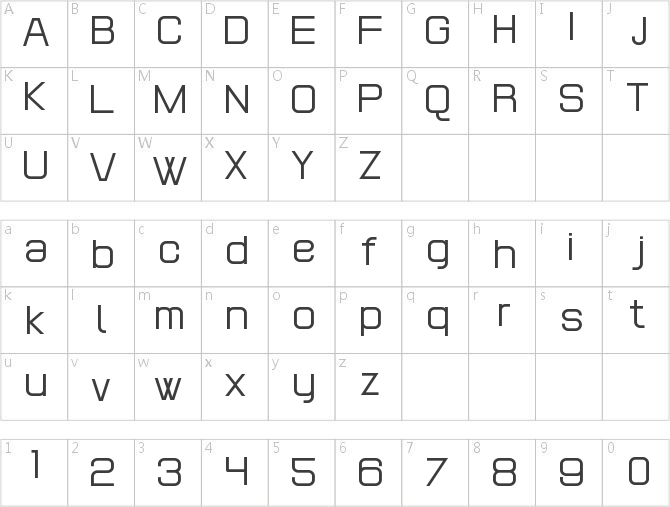
POE Headline Bold 詳情頁(yè)
POE Headline Bold字體字庫(kù)是一款讓人賞心悅目、百看不厭的英文字體,適合各類(lèi)廣告和產(chǎn)品包裝設(shè)計(jì)應(yīng)用,字體大小0.02MB,格式為ttf字體,上傳用戶是快霸中國(guó),作者/版權(quán)方為未知